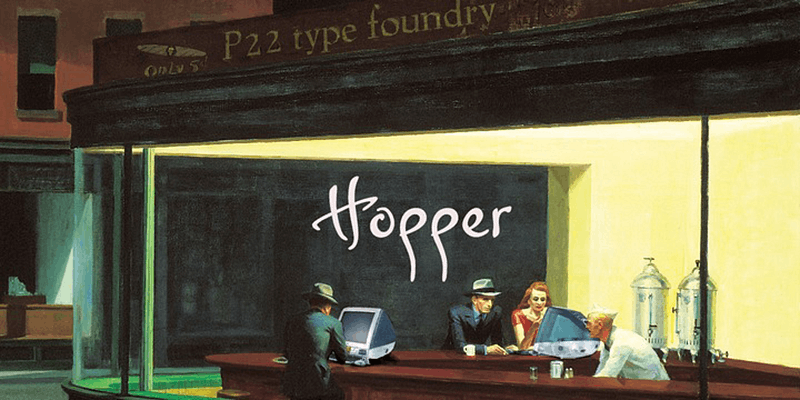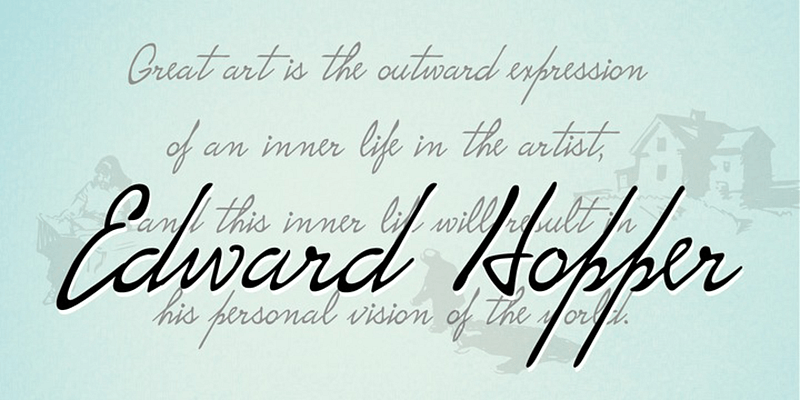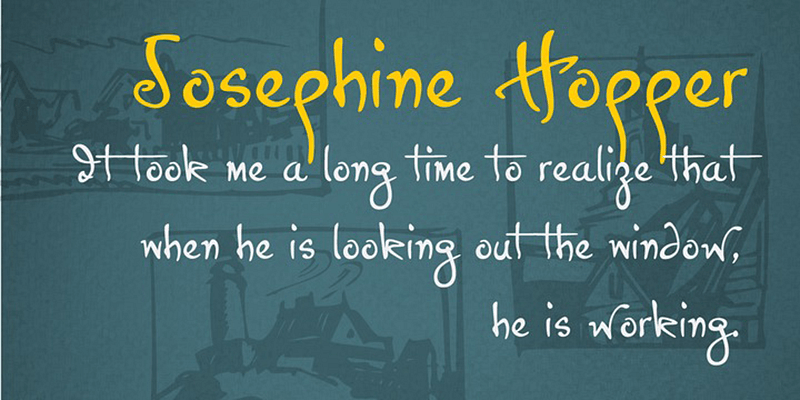
P22 Hopper Set si basa sugli stili di scrittura a mano dell’artista americano per eccellenza Edward Hopper e di sua moglie, Josephine Nivison Hopper.